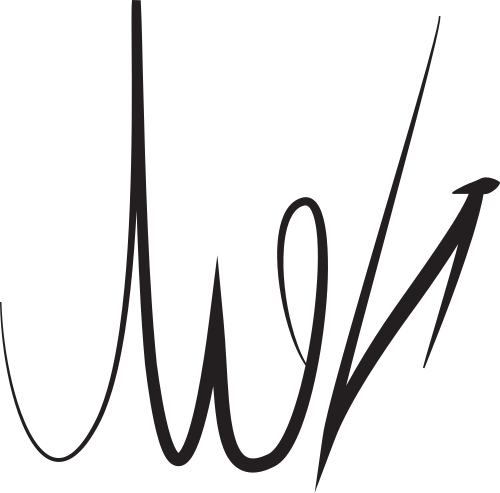
الأبجدية المقطعية للشيروكي
الأبجدية المقطعية الشيروكي ( بالشيروكي: ᏣᎳᎩ ᏗᎪᏪᎶᏙᏗ ، بالحروف اللاتينية: Tsalagi Digohwelodohdi ) هي أبجدية مقطعية ابتكرها سيكويا في أواخر العقد الثاني من القرن التاسع عشر وأوائل العقد الثالث منه لكتابة لغة الشيروكي . ويُعدّ ابتكاره لهذه الأبجدية المقطعية جديرًا بالذكر، إذ كان أميًا قبل ابتكارها. [ 3 ] بدأ سيكويا بتجاربه باستخدام الرموز التصويرية ، ثم تطور نظامه لاحقًا إلى الأبجدية المقطعية. في هذا النظام، يُمثّل كل رمز مقطعًا لفظيًا بدلًا من صوت واحد ؛ وتُوفّر الأحرف الـ 85 (كانت في الأصل 86) [ 1 ] طريقةً مناسبةً لكتابة لغة الشيروكي. تُشبه هذه الأحرف أحرفًا من أنظمة كتابة أخرى، مثل اللاتينية واليونانية والسيريلية والغلاغولية ، ولكنها لا تُستخدم لتمثيل الأصوات نفسها.
تاريخ
التاريخ المبكر
في حوالي عام ١٨٠٩، انبهر سيكويا بـ"الأوراق الناطقة" في اللغات الأوروبية المكتوبة، فبدأ العمل على ابتكار نظام كتابة للغة الشيروكي . بعد محاولته ابتكار رمز لكل كلمة ، أدرك سيكويا صعوبة ذلك، فابتكر في النهاية رموزًا تمثل المقاطع الصوتية. عمل على هذا النظام المقطعي لمدة اثنتي عشرة سنة قبل إتمامه، وتخلى عن معظم الرموز التي ابتكرها في البداية أو عدّلها.
بعد اكتمال نظام الكتابة المقطعي في أوائل عشرينيات القرن التاسع عشر، حقق شعبية شبه فورية وانتشر بسرعة في جميع أنحاء مجتمع الشيروكي. [ 4 ] وبحلول عام 1825، كان بإمكان غالبية الشيروكي القراءة والكتابة بنظام الكتابة الذي طوروه حديثًا. [ 5 ]
أدرك بعض معاصري سيكويا الأكثر علمًا على الفور أن الأبجدية المقطعية كانت اختراعًا عظيمًا. فعلى سبيل المثال، عندما رأى ألبرت غالاتين ، السياسي واللغوي المُدرَّب، نسخة من الأبجدية المقطعية لسيكويا، اعتقد أنها تتفوق على الأبجدية الإنجليزية لأنها تُسهِّل على الشيروكي اكتساب مهارات القراءة والكتابة في وقت لم يكن فيه سوى ثلث الناطقين بالإنجليزية يحققون هذا الهدف. [ 6 ] وأدرك أنه على الرغم من أن طالب الشيروكي مُطالب بتعلم 85 حرفًا بدلًا من 26 حرفًا في الإنجليزية، إلا أنه يستطيع القراءة فورًا بعد تعلم جميع الرموز. يستطيع طالب الشيروكي إنجاز ما قد يحتاجه طلاب الكتابة الإنجليزية عامين في غضون أسابيع قليلة. [ 7 ]
في عام ١٨٢٨، قام الكاتب والمحرر الشيروكي إلياس بودينو بتعديل ترتيب الأحرف في مخطط وأشكالها لتكييف الأبجدية المقطعية مع المطابع. [ ٨ ] وقد تم حذف الحرف السادس والثمانين بالكامل. [ ٩ ] بعد هذه التغييرات، اعتمدت صحيفة "شيروكي فينيكس" ، التي أصبحت فيما بعد "شيروكي أدفوكيت "، الأبجدية المقطعية ، ثم تبعتها صحيفة "شيروكي ميسنجر" ، وهي صحيفة ثنائية اللغة طُبعت في الإقليم الهندي في منتصف القرن التاسع عشر. [ ١٠ ]
في عام ١٨٣٤، أدخل صموئيل وورسيستر تعديلات على عدة أحرف لتحسين سهولة قراءة نصوص لغة الشيروكي. وكان أبرزها قلبه لحرف "دو" (Ꮩ) حتى لا يُخلط بينه وبين حرف "جو" (Ꭺ). [ ١١ ] وبخلاف ذلك، ظلت الأحرف ثابتة إلى حد كبير حتى ظهور تقنيات الطباعة الحديثة في القرن العشرين. [ ١٢ ]
التطورات اللاحقة
في ستينيات القرن العشرين، بدأت دار نشر شيروكي فينيكس بنشر الأدب باستخدام الأبجدية المقطعية للغة الشيروكي، بما في ذلك كتاب أغاني الشيروكي . [ 13 ] وفي أواخر سبعينيات القرن العشرين ، طُوِّرت كرة كتابة خاصة بالأبجدية المقطعية للغة الشيروكي لآلة الكتابة IBM Selectric . وقد ساهمت خطوط الحاسوب بشكل كبير في توسيع قدرة كتّاب الشيروكي على النشر بلغتهم. وفي عام 2010، طوّر روي بوني الابن وجوزيف إرب غطاءً للوحة مفاتيح الشيروكي، مما سهّل الكتابة بسرعة أكبر بهذه اللغة. ويستخدم الطلاب في مدرسة شيروكي نيشن للغمر اللغوي هذا الغطاء حاليًا، حيث تُكتب جميع المقررات الدراسية بالأبجدية المقطعية. [ 8 ]
في أغسطس/آب 2010، اقتنى معهد أوكونالوفيتي للفنون والثقافة في شيروكي، بولاية كارولاينا الشمالية، مطبعةً حروفيةً ، وأعاد صياغة حروف شيروكي المقطعية لبدء طباعة كتب ومطبوعات فنية فريدة من نوعها بهذه الحروف. [ 14 ] وفي 19 أكتوبر/تشرين الأول 2013، أنجز الفنانان جيف مارلي وفرانك برانون مشروعًا مشتركًا، استخدما فيه حروف شيروكي المقطعية من كلية ساوث وسترن كوميونيتي في مطبعة نيو إيكوتا . وكانت هذه المرة الأولى التي تُستخدم فيها الحروف المقطعية في نيو إيكوتا منذ عام 1835. [ 15 ]
يشهد نظام الكتابة المقطعية استخدامًا متزايد التنوع اليوم، بدءًا من الكتب والصحف والمواقع الإلكترونية وصولًا إلى لافتات الشوارع في تاهليكوا، أوكلاهوما ، وشيروكي، كارولاينا الشمالية . ويُطبع عدد متزايد من أدب الأطفال بلغة الشيروكي لتلبية احتياجات الطلاب في مدارس الانغماس اللغوي في أوكلاهوما وكارولاينا الشمالية. [ 16 ] وقد ظهرت هذه اللغة على ربع دولار أمريكي صدر عام 2023 تخليدًا لذكرى ويلما مانكيلر .
التأثير المحتمل على نظام كتابة فاي الليبيري
في ستينيات القرن العشرين، ظهرت أدلة تشير إلى أن الأبجدية المقطعية لشعب الشيروكي في أمريكا الشمالية شكلت نموذجًا لتصميم الأبجدية المقطعية لشعب الفاي في ليبيريا. [ 17 ] ظهرت الأبجدية المقطعية لشعب الفاي حوالي عامي 1832-1833. تزامن ذلك مع سعي المبشرين الأمريكيين لاستخدام الأبجدية المقطعية لشعب الشيروكي كنموذج لكتابة اللغات الليبيرية. [ 18 ] ويبدو أن هناك صلة أخرى تتمثل في هجرة بعض أفراد الشيروكي إلى ليبيريا بعد اختراع الأبجدية المقطعية لشعب الشيروكي (التي انتشرت بسرعة بينهم في سنواتها الأولى) ولكن قبل اختراع الأبجدية المقطعية لشعب الفاي. أحد هؤلاء الرجال، أوستن كورتيس، تزوج من عائلة بارزة من شعب الفاي وأصبح زعيمًا مهمًا لهم. كما يبدو أن هناك صلة بين شكل مبكر من لغة الباسا المكتوبة والأبجدية المقطعية لشعب الشيروكي الأقدم. [ 19 ]
وصف
يتألف نظام الكتابة الحديث من 85 حرفًا، يمثل كل منها مقطعًا لفظيًا مميزًا . تمثل الأحرف الستة الأولى مقاطع صوتية منفردة من حروف العلة. تليها أحرف تمثل مقاطع صوتية مركبة من حروف ساكنة وحروف علة.
تُظهر الجداول أدناه الأبجدية المقطعية بترتيب التلاوة، من اليسار إلى اليمين، ومن الأعلى إلى الأسفل، كما رتبها صموئيل وورسيستر ، إلى جانب ترجماته الصوتية الشائعة الاستخدام. [ 20 ] [ 21 ] وقد لعب دورًا محوريًا في تطوير الطباعة الشيروكية من عام 1828 حتى وفاته عام 1859. يُمثل الحرف اللاتيني "v" في النسخ، كما هو موضح في العمود الأخير، حرف العلة الأنفي الأوسط المركزي ، /ə̃/ .